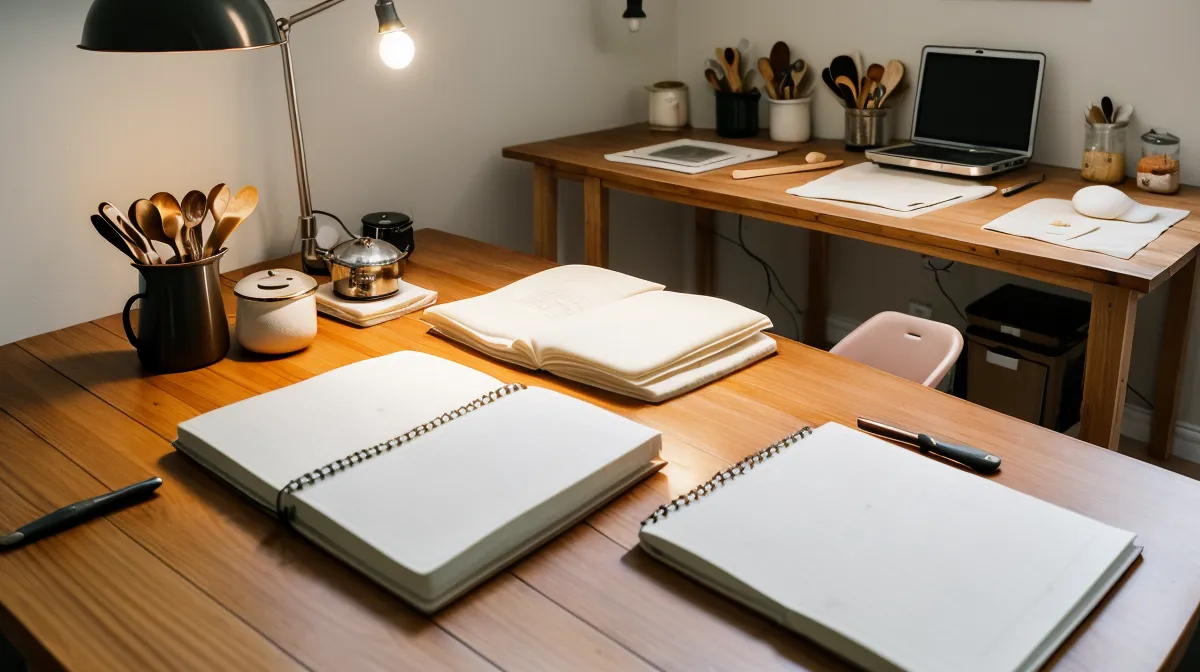
Der Schmerz sitzt immer an derselben Stelle: ein Fingerbreit rechts der Wirbelsäule, mitten zwischen den Schulterblättern, genau dort, wo sich beim Brush Lettering die Zugkraft jedes Abstrichs bündelt. Wer den Küchentisch zum Atelier erklärt und jeden Handlettering-Kurs mit derselben Beharrlichkeit durcharbeitet wie ein Backrezept, merkt irgendwann: Ergonomie ist kein Nebenthema, sie entscheidet darüber, ob aus stundenlangem Üben tatsächlich Brushlettering-Fortschritt wird oder nur ein verspannter Nacken.
Ergonomie am Küchentisch: Zwei Haltungen im Vergleich
Zwei Setups stehen sich in meinem Küchentisch-Atelier in Bonn-Beuel gegenüber. Das eine ist die klassische Haltung: Papier parallel zur Tischkante, Rücken gerade, Blick von oben senkrecht auf das Blatt. Das andere ist jene Haltung, zu der ich nach etlichen Abenden mit schmerzendem Nacken gewechselt bin: Papier um 45 Grad gedreht, Ellenbogen locker nach außen, linke Hand aktiv als Anker. Beide Varianten habe ich wiederholt gegeneinandergestellt, auf demselben runden Esstisch mit den Schneidematten-Kratzern in der Holzoberfläche, unter dem Regal mit den sortierten Tintengläsern und Federrollen.
In den Kursvideos meines aktuellen Handlettering Kurses gleiten die Dozentinnen fast schwerelos über das Blatt. Am eigenen Tisch sieht das anders aus. Ein Tisch von 75 Zentimetern Höhe zwingt die meisten Menschen dazu, den Oberkörper leicht nach vorn zu neigen, um genug Druck auf den Brush Pen zu bringen, und bei glattem 90-Gramm-Papier ist der Widerstand ohnehin gering – was sich auch auf die Druckkurve auswirkt und dazu verleitet, Stabilität allein aus der Schulter zu holen statt aus einem locker aufliegenden Unterarm.
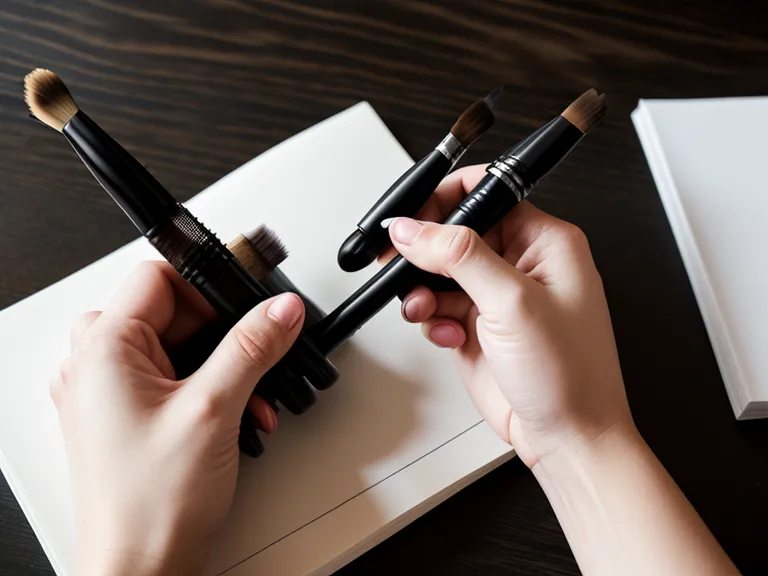
Warum die klassische Sitzhaltung nach Stunden schmerzt
Genau diese fehlende Rumpfstabilität war es, die bei mir zu blau gedrückten Fingerkuppen führte, lange bevor der eigentliche Rückenschmerz auftauchte. Dickes Aquarellpapier für Trockenübungen habe ich inzwischen aus dem Regal verbannt: Die raue Textur erhöht den Widerstand spürbar und lässt die Hand schneller verkrampfen als glatte Oberflächen. Der Wechsel zum glatten Papier war ein erster Schritt, die Sitzhaltung blieb aber das eigentliche Problem – ein Blick in den Spiegel während einer Übungssession zeigte eine Schulter, die spürbar höher stand als die andere, während die Tischdecke darunter längst mehr Tinte als Muster zeigte.
Papier drehen, Schulter senken
Die zweite Haltung setzt genau da an. Der Ansatzwinkel der Pinselspitze braucht rund 45 Grad zum Papier, um den Kontrast zwischen kräftigen Abstrichen und hauchdünnen Aufstrichen zu erreichen, ohne die Spitze zu ruinieren – darüber sind sich die meisten Kursleiterinnen einig. Seltener erklärt wird, was passiert, wenn nicht der Stift, sondern das ganze Blatt um denselben Winkel gedreht wird: Der Ellenbogen wandert von selbst nach außen, die Schulter sinkt ab, der Oberkörper muss sich nicht mehr über das Papier beugen. Wer mit Begriffen wie Ober- und Unterlänge oder Serife noch fremdelt, findet passende Erklärungen im Glossar der Buchstaben-Anatomie – hier geht es nur um die Haltung, nicht um die Anatomie der Buchstaben selbst.
Meine Bekannte Christine Albers vom Bonner Kreativ-Stammtisch hat mir das nicht geglaubt, bis sie es selbst ausprobiert hat. Erklärungen überzeugen sie ohnehin selten, sie dreht lieber sofort am eigenen Blatt, bis sich etwas richtig anfühlt, statt sich ein Tutorial nach dem anderen anzusehen. Der Unterschied zwischen den beiden Haltungen lässt sich ohnehin am schnellsten so spüren: nicht durch Zusehen, sondern durch den direkten Vergleich am eigenen Tisch.
Der Unterschied zeigt sich nicht nur im Nacken, sondern auch auf dem Papier selbst. Eine ganze Zeile Versalien in gleichmäßigem Winkel und Abstand, ganz ohne Lineal gezogen, ist inzwischen keine Ausnahme mehr, sondern die Regel, seit ich auf die gedrehte Haltung setze – ein Nebeneffekt, den ich der ruhigeren Schulter zuschreibe, nicht einer plötzlich besseren Technik.
Welche Rolle spielt die nicht dominante Hand?
Von der Schreibhand ist in Kursen fast immer die Rede, von der anderen kaum. Ich nenne sie die Geisterhand, weil sie unauffällig einen großen Teil der Stabilität übernimmt. Führt die linke Hand das Papier nicht aktiv, muss die rechte doppelte Arbeit leisten: schreiben und gleichzeitig das Blatt gegen den Druck des Stifts sichern. Krämpfe sind die Folge, oft erst mit Verzögerung spürbar.
Sobald die linke Hand flach auf dem oberen Drittel des Blattes liegt, entspannt sich der Nacken fast von selbst – eine Ankerfunktion, die selbst in einem ausführlichen Vergleich verschiedener Kursstrukturen kaum vorkommt, weil dort meist nur von der Schreibhand die Rede ist. Starrheit ist dabei der eigentliche Feind: Wer stur versucht, eine einzige richtige Position zu halten, züchtet sich die nächste Verspannung selbst heran. Häufige Mikrobewegungen – das Becken leicht verschieben, die Finger alle paar Minuten lockern – gleichen die einseitige Belastung zuverlässiger aus als jede starre Idealhaltung.
Kurze Einheiten oder lange Sessions – welches Setup passt wann?
Meine Nachbarin Elisabeth Rudert übt jeden Tag, aber nie länger als zwanzig Minuten am Stück. Für sie reicht die klassische, parallele Papierhaltung meistens aus, weil sich Fehlbelastung in so kurzen Einheiten kaum aufsummiert. Bei mir sieht das anders aus: Ganze Nachmittage mit Copperplate-Übungen oder mehrstündige Blöcke am Wochenende summieren jede kleine Fehlhaltung zu echtem Schmerz. Wie viel Übungsvolumen für sichtbaren Fortschritt nötig ist, hängt von so vielen Faktoren ab, dass es ein eigenes Thema für sich bleibt – hier geht es nur darum, wie sich die reine Übungszeit auf den Rücken auswirkt, unabhängig vom Tempo des Fortschritts.
Welches Papier zur eigenen Stifthaltung passt, ist am Ende eine Frage der Papier-Stift-Kompatibilität, die jede Handlettering-Person für sich selbst austesten muss – und die Haltung wirkt sich nebenbei auch auf die Brushpen-Abnutzung aus, weil ungleichmäßiger Druck die Spitzen schneller ausfranst. Wer zwischen digitalen und gedruckten Übungsformaten schwankt, sollte bedenken, dass ein Tablet auf Augenhöhe für den Nacken freundlicher ist als der ständige Blick nach unten auf eine gedruckte Vorlage. Wer noch unentschieden ist, welches Format zu einem passt, findet im Vergleich zum Handlettering Kurs mit Video oder PDF unterschiedliche Antworten auf genau diese Frage – Ergonomie sollte dabei mindestens so viel Gewicht bekommen wie Inhalt oder Preis.